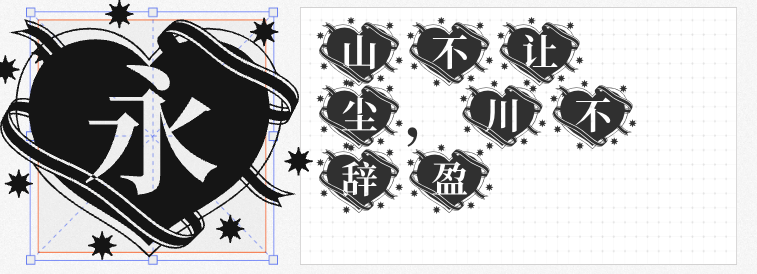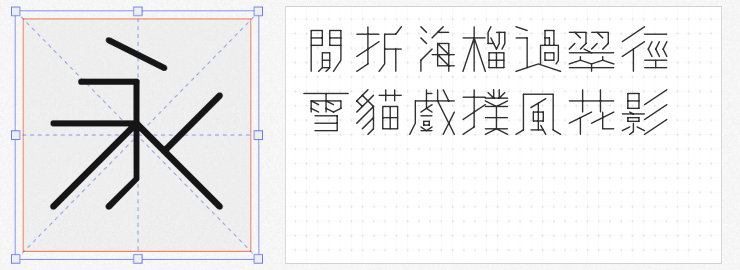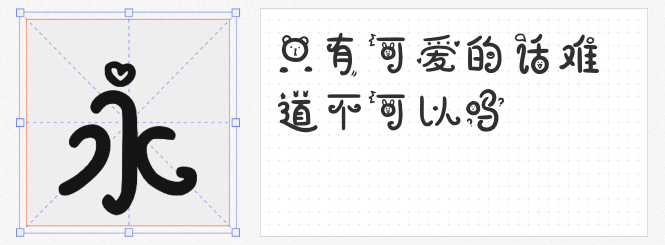
在设计的世界里,字体不仅是信息传递的载体,更是情感与风格的塑造者。今天,就为大家推荐四款既免费商用又创意满满的字体,它们各自拥有独特的魅力,能够为你的设计作品增添无限活力。
1. 庞门正道轻松体
这款字体以其可爱蠢萌、俏皮十足的风格,迅速俘获了众多设计师的心。字形活泼灵动,仿佛每一个字都在跳跃,非常适合用于宠物、儿童等相关设计,让作品瞬间充满童趣与温馨。
2. 千图小兔体
将可爱的小兔形象巧妙融入字体之中,千图小兔体尽显年轻、活力与俏皮。无论是可爱风的海报,还是少女心的店招,它都能完美驾驭,为设计增添一抹亮色,让人过目难忘。
3. 思源宋体花样心纹
基于思源宋体粗体改造,这款字体在保留宋体优雅韵味的同时,巧妙地加入了花样心纹装饰。它不仅适用于标题设计,为文字增添艺术感,还能作为图片水印,让作品在细节处彰显独特品味。虽然不适合大篇幅文章,但在特殊场合下,它绝对能成为点睛之笔。
4. 黄令东细线体
这款字体以其几何感十足、笔画直来直去的特点脱颖而出。通过程序自动生成,结合递归根式包装语言编写,黄令东细线体展现了科技与艺术的完美结合。值得注意的是,它采用繁体词根设计,输入简体字会自动映射为繁体字形,为设计增添一份古典韵味。适用于追求简约、现代感的设计场景,让作品在简洁中不失格调。
这四款免费商用的创意字体,每一款都独具匠心,能够满足不同设计需求。无论是追求可爱、活力,还是艺术、科技感,它们都能成为你设计路上的得力助手。